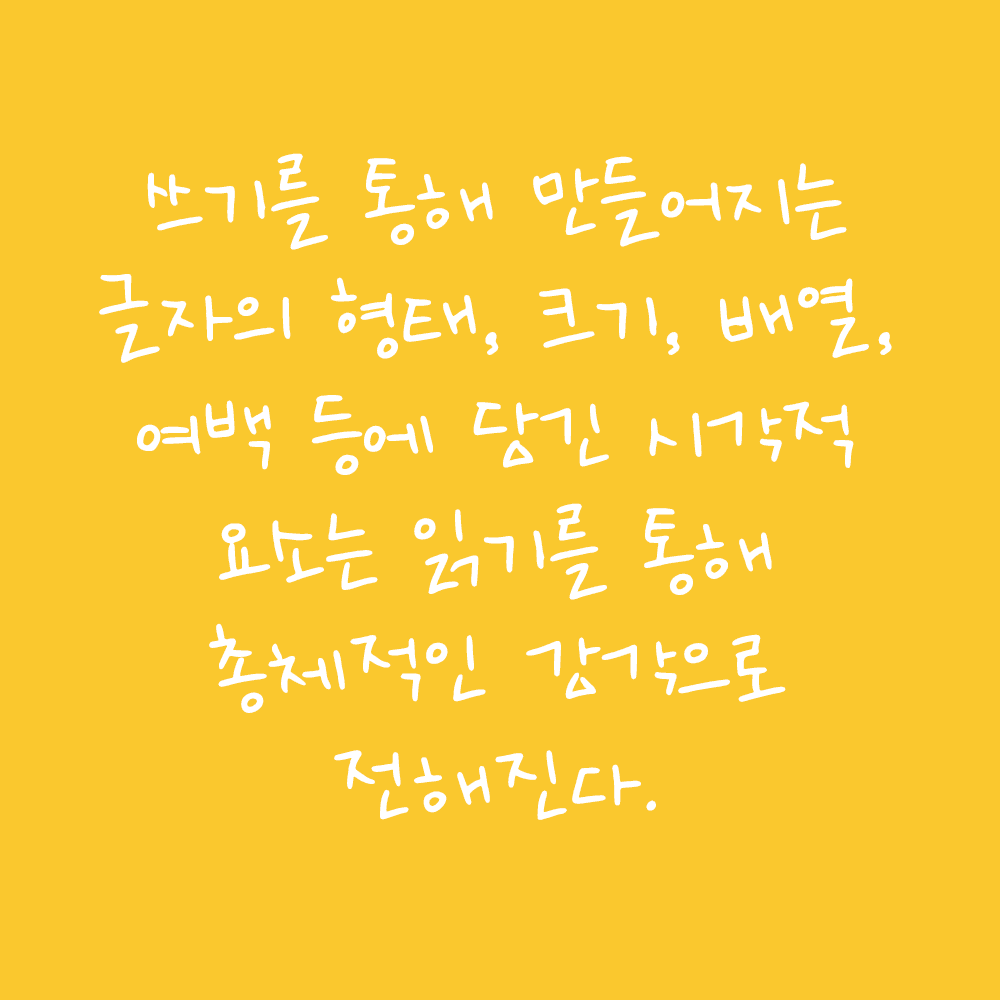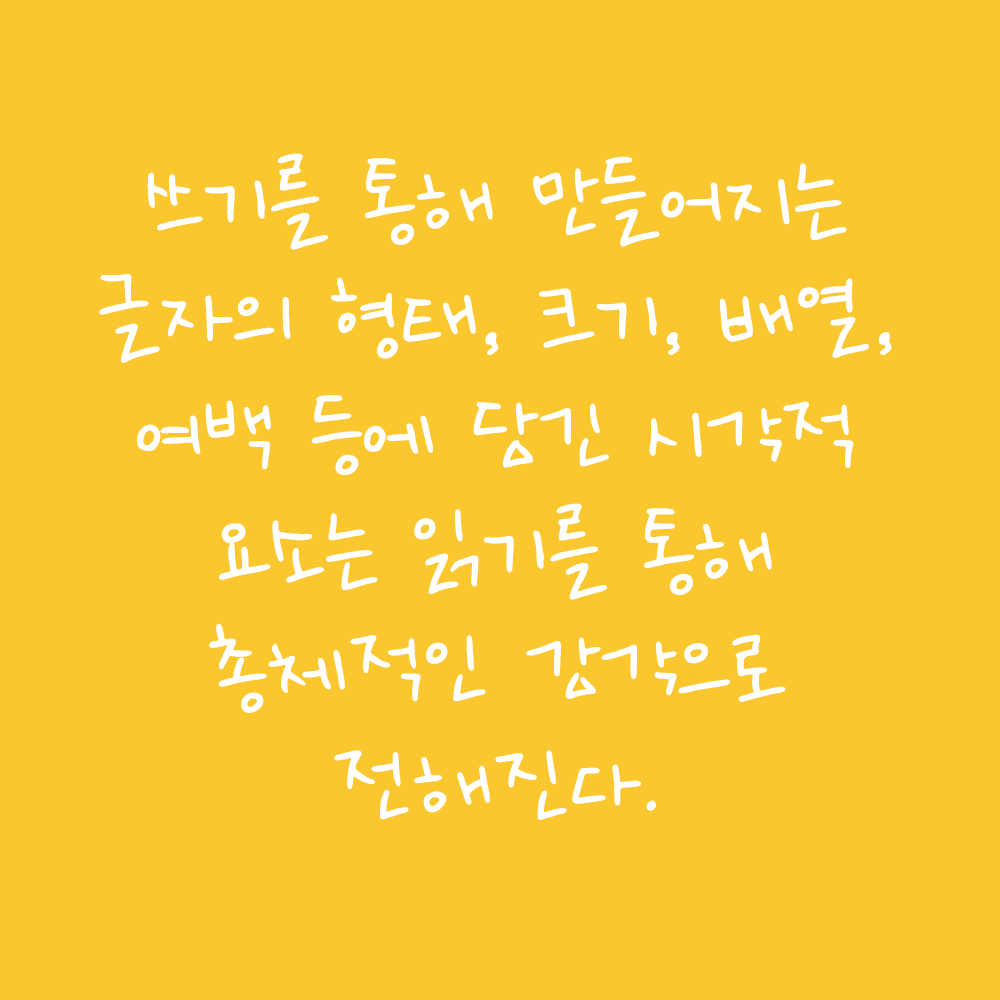
그리운X국한박 신고양이
GriunXHangeul Shin Cat
그리운X국한박 신고양이 소개
제5회 한글실험프로젝트 《글(자)감(각): 쓰기와 도구》 The 5th Hangeul Design Project 《Senses of Writing: Tools & Perception》 전시기간: 2025.11.19.~2026.3.22. 전시장소: 문화역서울284 RTO 주최·주관: 국립한글박물관 이 손글씨 폰트는 국립한글박물관 제5회 한글실험프로젝트 《글(자)감(각): 쓰기와 도구》 전시 연계 이벤트를 통해 제작되었습니다. 손의 움직임과 쓰는 감각을 그대로 담아, 쓰기의 경험을 폰트로 확장합니다.